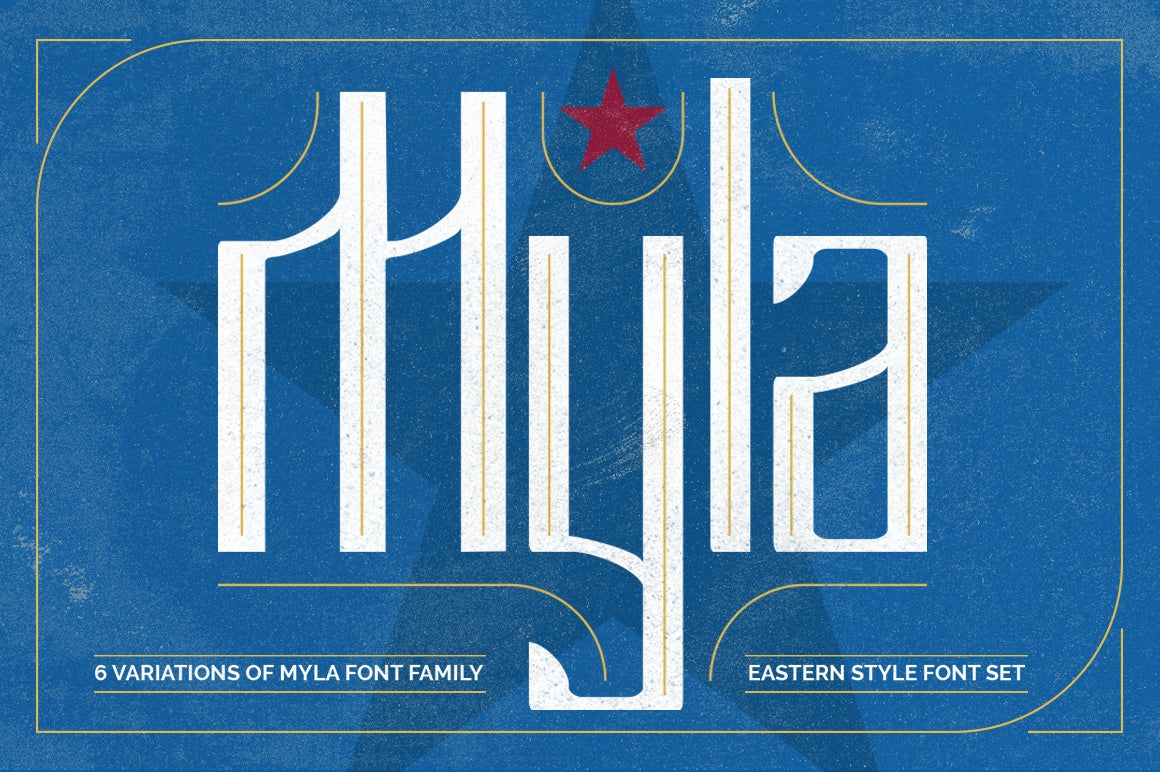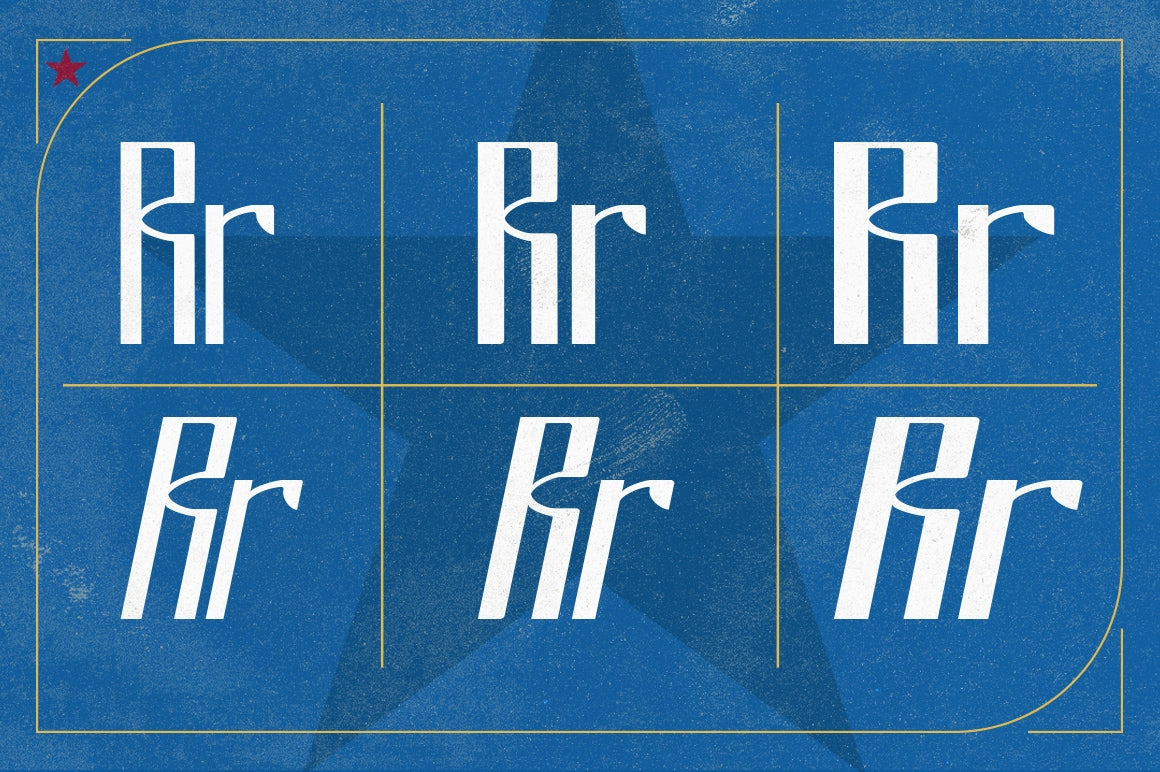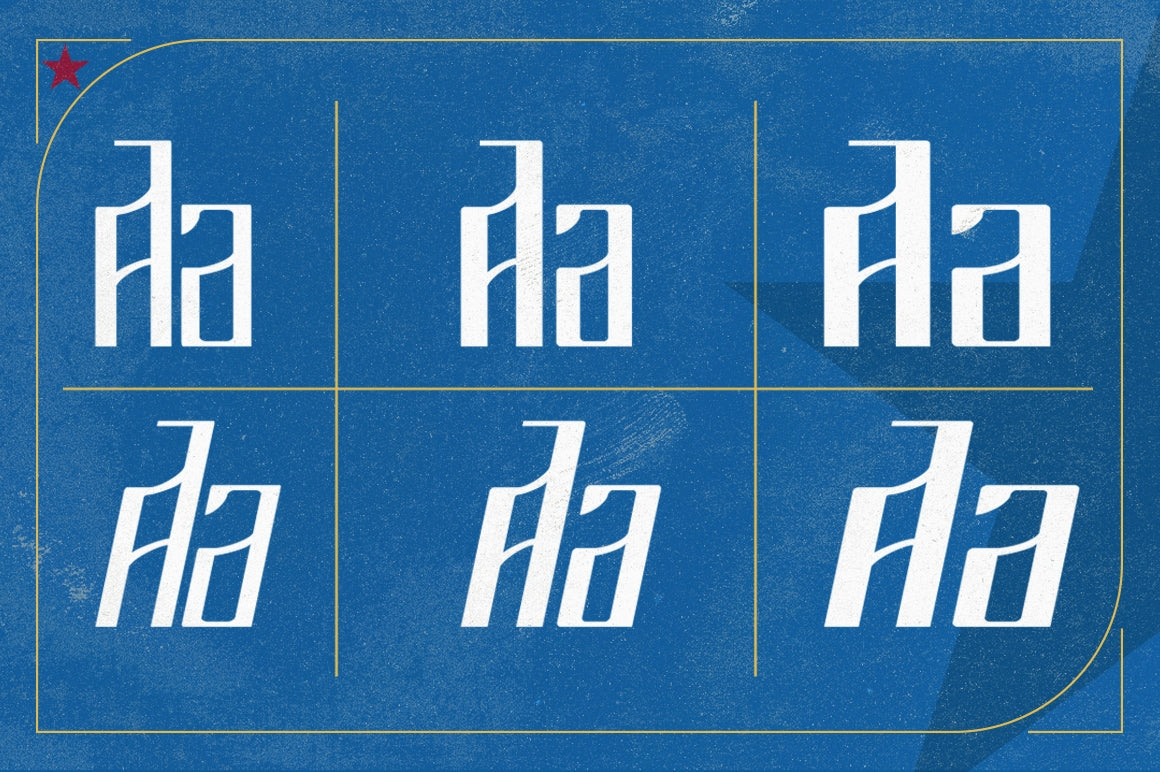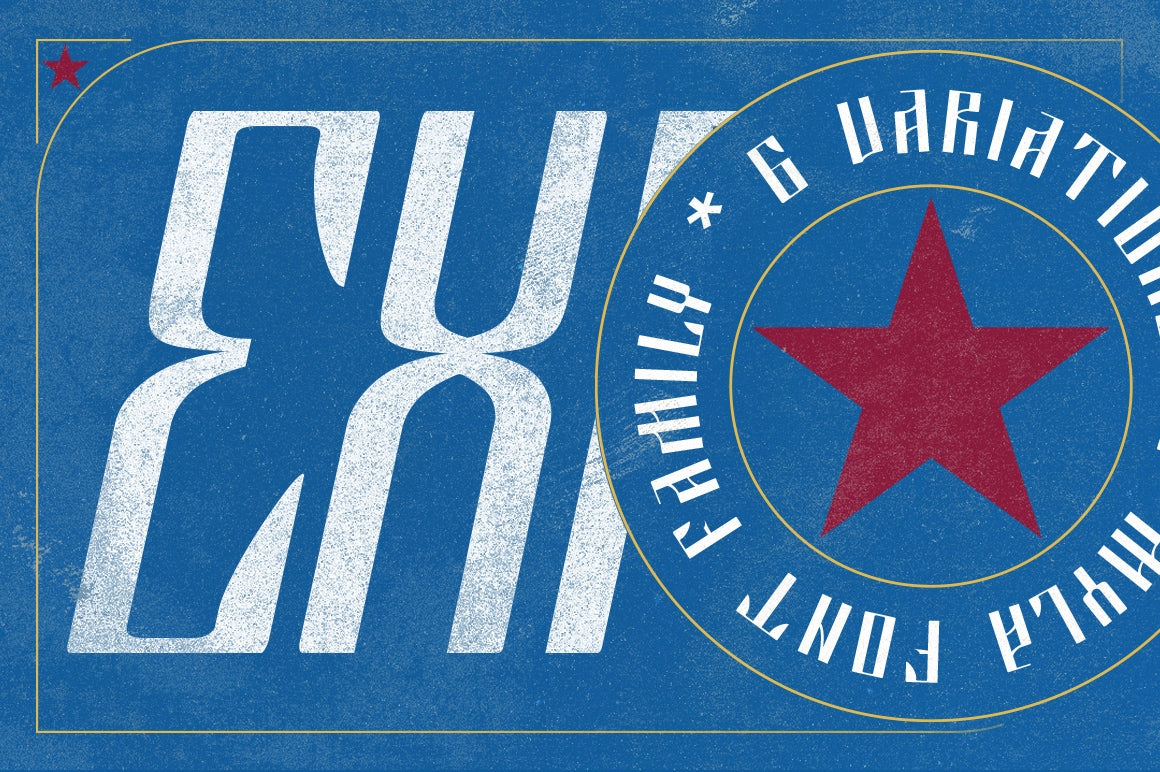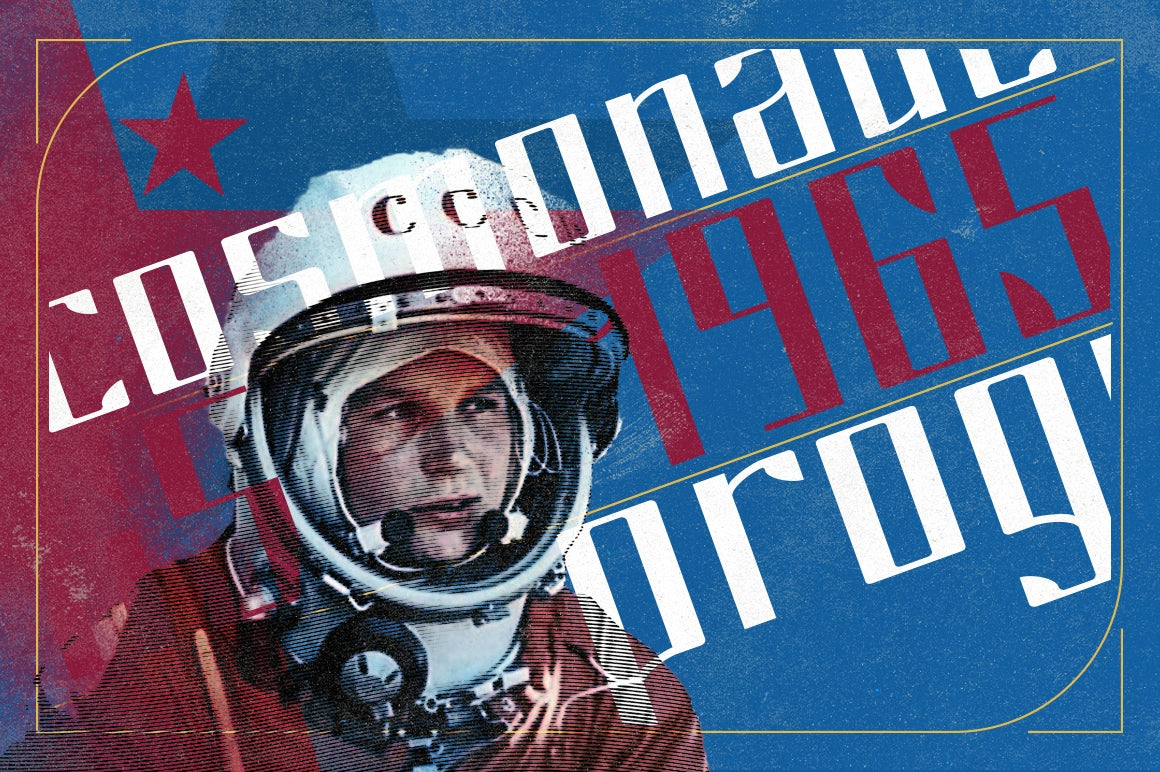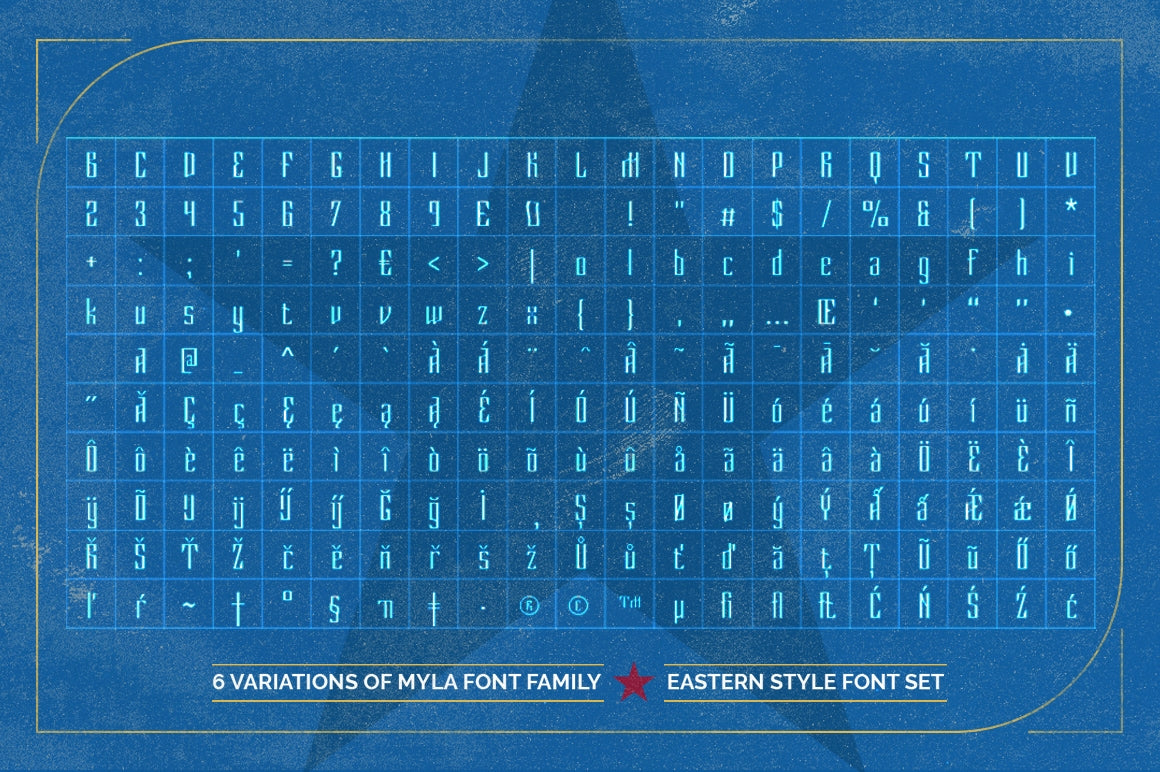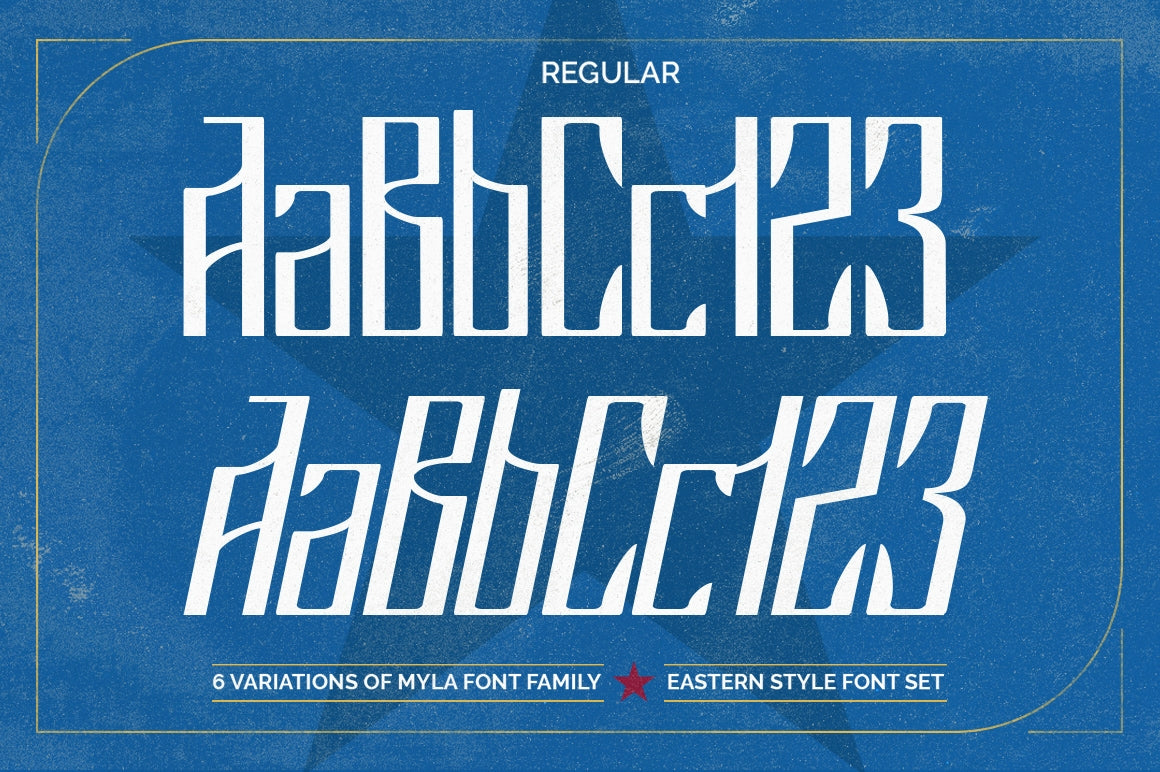
Fuente Myla
Con la fuente Myla, puedes transmitir tu mensaje fácilmente en tu diseño. Usa su estilo oriental de inspiración soviética para crear diseños impactantes en exhibiciones, etiquetas, ropa, escenas de cine, pósteres, títulos de películas, conciertos, portadas de álbumes, logotipos y mucho más.
Disponible en 3 estilos: Regular, Negrita y Negro, con 2 variantes: regular y cursiva. Inspirada en la Pascua y la tradición soviética, la gente trabajadora y la década de 1960, es ideal para proyectos retro y vintage, desde diseños claros hasta diseños de aspecto rústico.
La fuente Myla se caracteriza por:
Alternativas estilísticas
Ligaduras
Caracteres internacionales (multilingües)
Símbolos de puntuación
Características de OpenType
Soporte multilingüe: inglés, albanés, danés, holandés, estonio, croata, bosnio, esloveno, finlandés, francés, alemán, islandés, italiano, noruego, portugués, español, sueco y muchos otros idiomas; consulte la lista completa de caracteres.